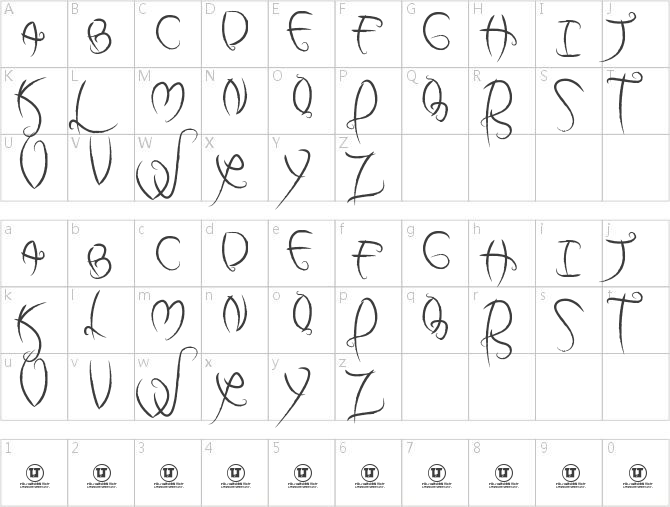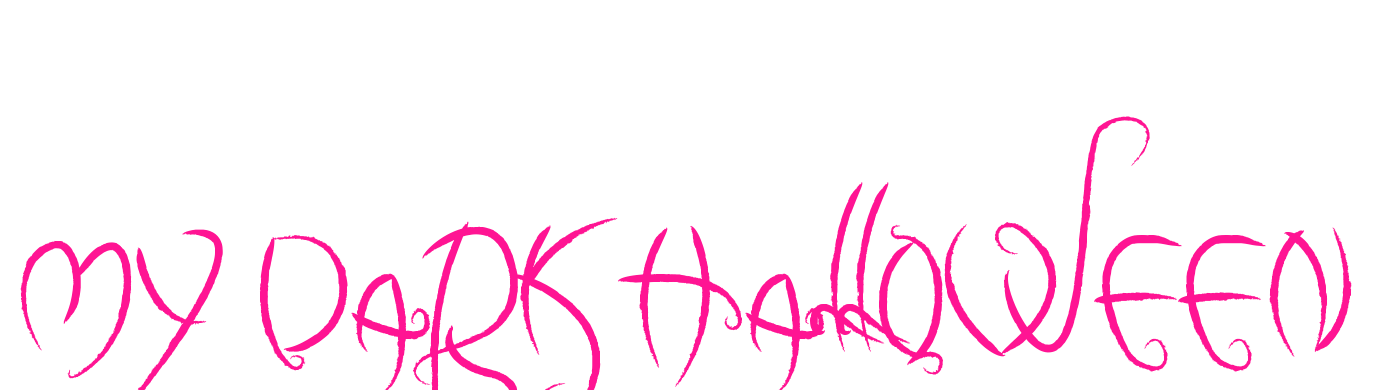
my dark halloween
my dark halloween字體字庫(kù)是一款讓人賞心悅目、百看不厭的英文字體,適合各類(lèi)廣告和產(chǎn)品包裝設(shè)計(jì)應(yīng)用,字體大小0.48MB,格式為ttf字體,上傳用戶是Elieen,作者/版權(quán)方為未知